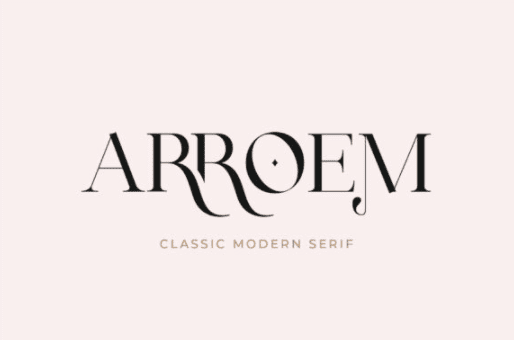
Название: Arroem Font (2021)
Arroem - это стильная смесь современного и классического шрифта с засечками.
Он позволяет создавать потрясающие дизайны, так как способен украсить любое творение!
Название: Arroem Font (2021)
Arroem - это стильная смесь современного и классического шрифта с засечками.
Он позволяет создавать потрясающие дизайны, так как способен украсить любое творение!